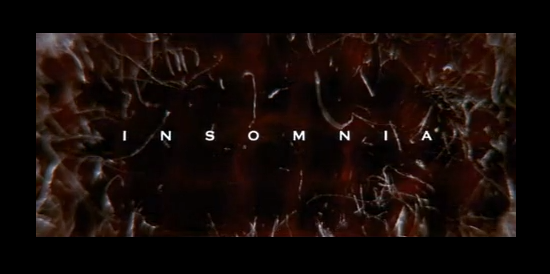
Welche Schrift? INSOMNIA Vorspann
Ich mal wieder ... Google will mir nicht sagen um welche Schrift es sich hier handelt:
Ich als Nicht-Typograf hab erst an eine Art Copperplate ohne Serifen gedacht. äh ... Nein.
Gotham ist es auch nicht. Habt ihr eine Idee?
Gotham?
Ohne mir jetzt die HD-Version mit der Lupe angesehen zu haben, würde ich dennoch behaupten, dass es sich hierbei in der Tat um eine Copperplate handelt. Denn die nachfolgenden »Credits« deuten ebenfalls darauf hin: